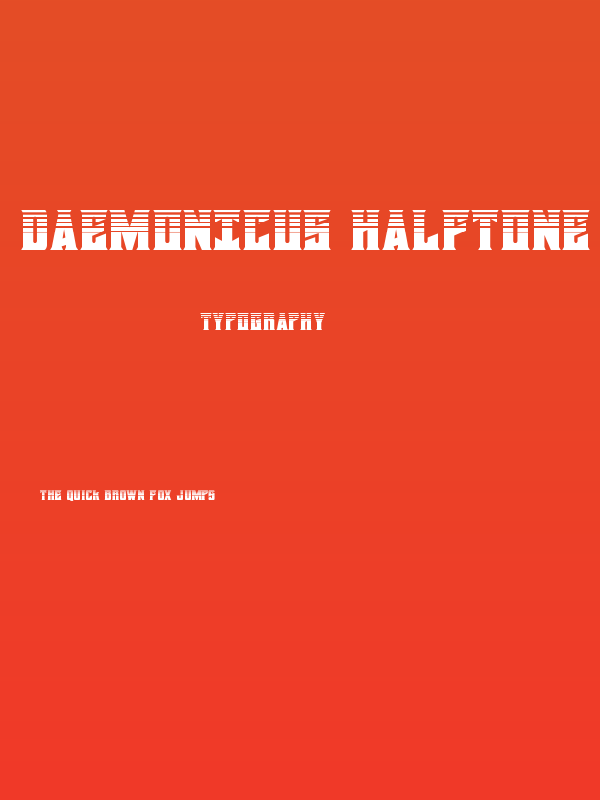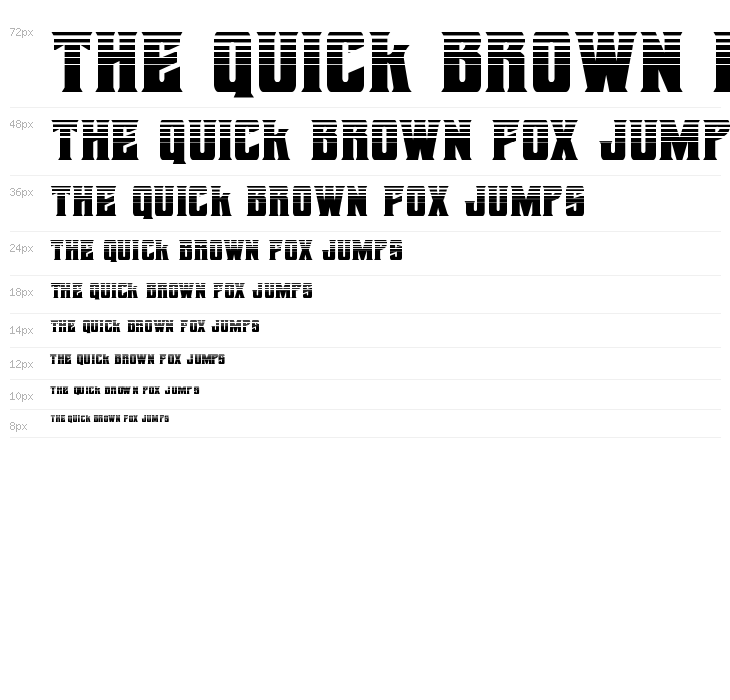
Daemonicus Halftone Font
✎ Thick
| Vorgeschlagene Projekte | Ideal for posters, album covers, branding, and any project needing a bold, dramatic typeface. |